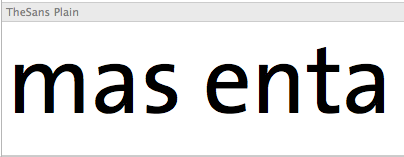
a sieht aus wie eine Myriad aber ...
... hat ein doppelstöckiges g
davon habe ich aber kein gutes Bild ...
Leider hat mir What-the-Font nichts passendes ausgespuckt?
Weiss jemand was es ist? DANKE
hier sieht man das g - das kleine p (klebt ganz links) ist noch etwas spezieller ansonsten sehe ich keine Unterschiede
Wenn ich mir das Bild oben auf der Seite von masventa anschaue würde ich sagen es ist die Thesis.
Die Thesis ist es auf keinen Fall.
täuschen mich da meine altersschwache Augen oder sind das zwei verschiedene Schriften? Speziell die Buchstaben a und t fallen mir besonders auf. Das zweite Bild sieht mach TheSans aus, das erste nach Myriad.
Die Thesis ist es auf keinen Fall.
Vielleicht hätte ich es auch mit einem Bild machen sollen. Hier das was ich meinte:
Das schon, ja, aber darum geht es ja nicht 8) .
Er schrieb "Wenn ich mir das Bild oben auf der Seite von masventa anschaue würde ich sagen es ist die Thesis." Und das Bild oben auf der Seite ist jenes was im allerersten post gezeigt ist:
Und das ist nicht die Thesis.
Oh. Ich glaube hier geht gerade einiges durcheinander. Was ich mit Bild oben auf der Seite meinte ist das was ich dann auch gezeigt hatte - nicht das Logo. Schliesslich war ja auch die Frage nach einem doppelstöckigem g. Da es das im Wort Masventa nicht gibt bin ich auf die Seite gegangen und das erste doppelstöckige g was ich gesehen habe war in dem Bild was ich gepostet habe. und das scheint ja nun die Thesis zu sein. Zum Logo-Schriftzug würde ich auch sagen das es Myriad ist.
Es ging mir schon um die Schrift mit dem doppelstöckigen g (also die Thesis), habe aber das andere Bild gepostet, da es besser lesbar war und ich auf den ersten Blick dachte, es wäre die gleiche Schrift.